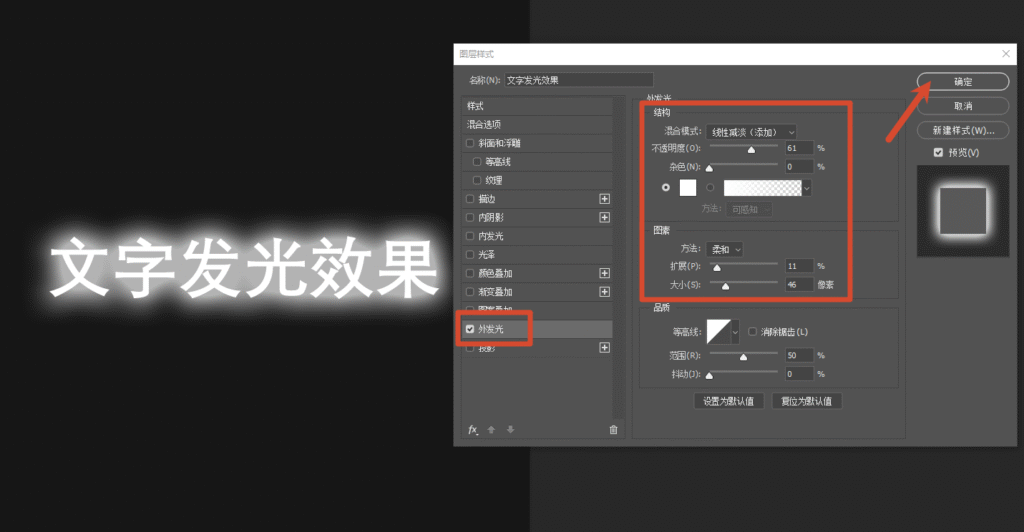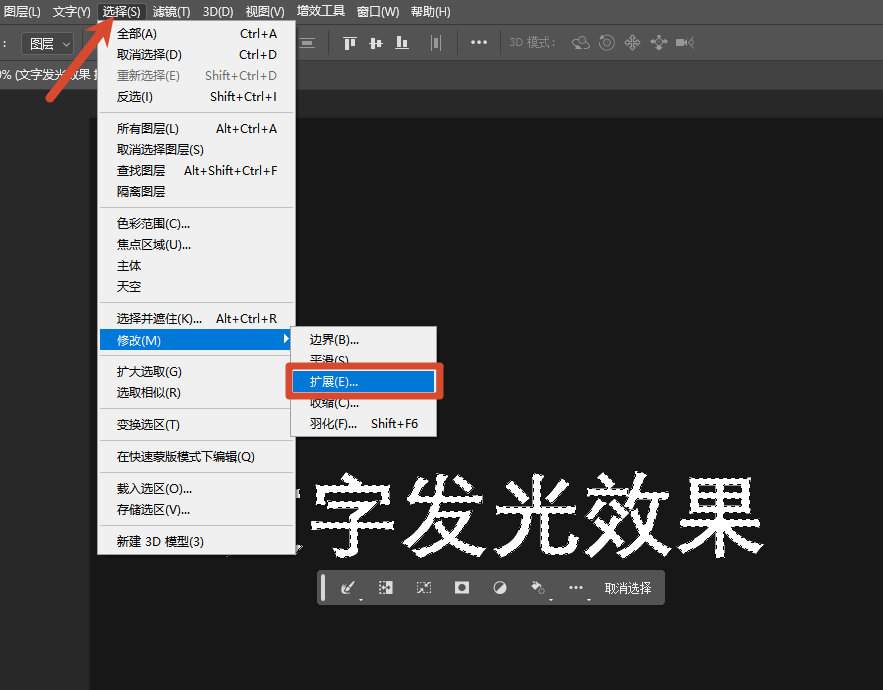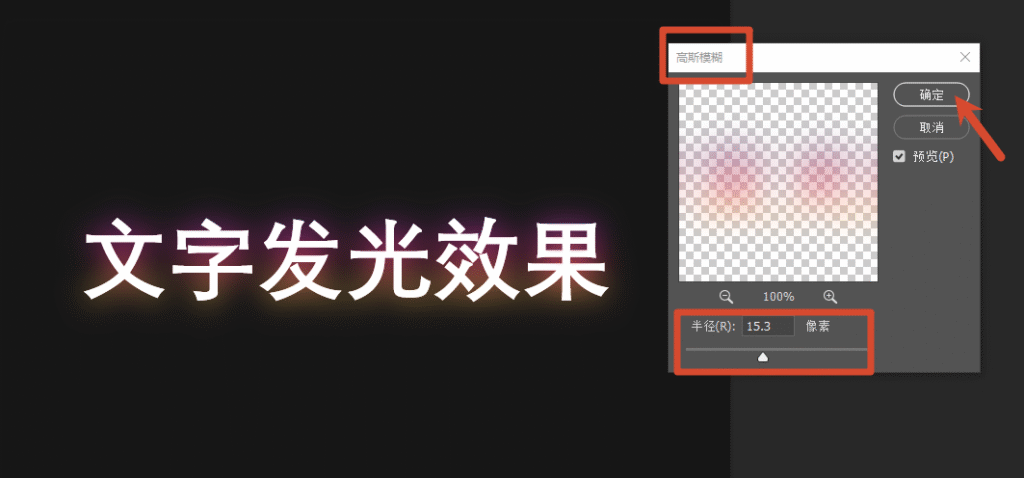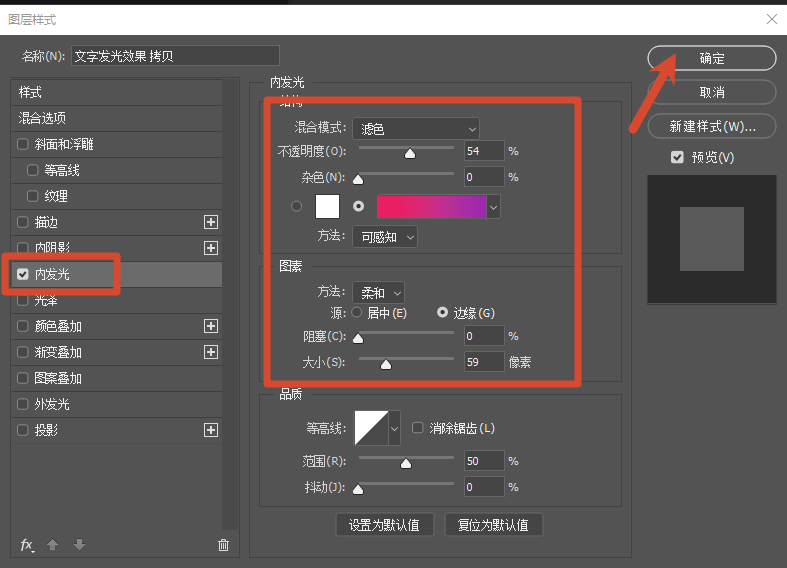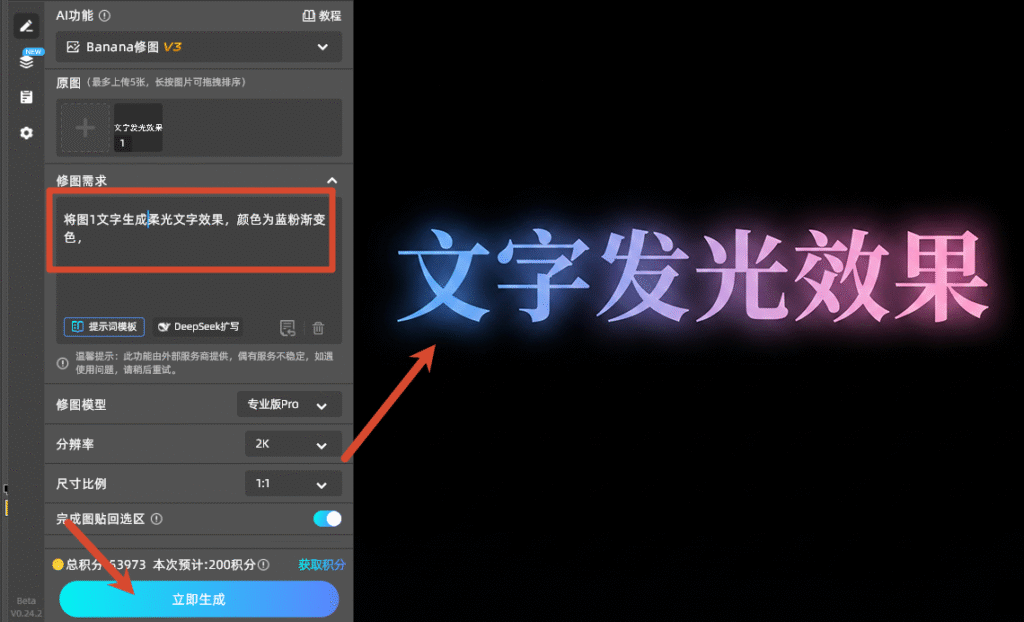
PS发光字体效果怎么做?3种方法从零教学
在海报设计、短视频封面、电商主图、赛博朋克风配图中,发光字体是提升画面氛围感、突出文字主体的常用特效。很多设计新手常常疑惑:ps发光字体效果怎么做?ps怎么做出自然不生硬的文字光晕?ps霓虹灯发光字体怎么制作?
本文结合专业设计实操经验,分享3种实用的PS发光字体制作方法,包含基础简易发光、高级霓虹发光、AI一键智能发光,适配PS2020-2026全版本,兼顾新手零基础操作和专业精细化调色,同时推荐高效便捷的StartAI插件,解决新手做光效卡顿、质感差、参数难调的痛点。
一、PS基础外发光制作:新手零基础简易发光字体
这是最简单、最通用的ps字体发光制作方法,依托PS自带图层样式,无需复杂操作,适合做简约柔光、日常海报发光文字,也是新手入门必学方法,适配绝大多数纯色背景、简约设计场景。
操作详细步骤:
新建画布输入文字:打开PS软件,快捷键Ctrl+N新建画布,建议深色背景(黑色、深灰色更凸显发光质感);点击左侧文字工具(T),输入需要制作特效的文字,调整字体、字号、字间距,优先选用粗体无衬线字体,发光层次感更强。
打开图层样式面板:鼠标双击右侧文字图层空白区域,弹出图层样式设置窗口,勾选左侧菜单栏中的外发光选项,这是制作基础发光的核心功能。
调整发光核心参数:混合模式推荐选择【线性减淡(添加)】,发光质感通透不发灰;不透明度控制在40%-75%,避免光线过曝;扩展数值5-15像素,模糊光晕边缘;大小根据文字尺寸调整,小字10-25像素、大字30-60像素。
调整图层模式参数
保存导出成品:参数调试完成后点击确定,简单的柔光发光字体就制作完成,快捷键Ctrl+Shift+S保存图片,支持PNG透明背景格式。
新手避坑技巧:很多人做的发光字体生硬廉价,核心原因是不透明度过高、发光颜色饱和度超标,日常设计建议选用低饱和柔光色。
二、进阶高级教程:PS霓虹灯发光字体效果
想要制作赛博朋克、夜店风、电竞风炫酷霓虹灯发光字体,单纯依靠外发光无法实现通透双层光感,需要结合选区修改、高斯模糊、图层混合模式制作,适合海报、Banner、短视频封面等高颜值设计场景。
操作详细步骤:
预处理文字图层:输入文字并排版完成,右键文字图层选择【栅格化文字】,将文字转为像素图层;按住Ctrl键点击图层缩略图,载入选区。
扩展制作光晕底衬:顶部菜单栏选择【选择-修改-扩展】,扩展量设置8-12像素,新建空白图层放置在文字下方,填充霓虹主色调。
选择-修改-扩展
模糊优化光效质感:选中光晕图层,点击【滤镜-模糊-高斯模糊】,模糊半径15-30像素,修改图层混合模式为【线性减淡】,强化发光通透感。
滤镜-模糊-高斯模糊
叠加细节光效:回到原文字图层,添加内发光图层样式,搭配深蓝色、玫红色等高饱和霓虹色,叠加渐变效果,打造双层光影层次感。
图层样式—内发光
痛点总结:进阶方法参数繁琐,需要反复调试模糊数值、混合模式,新手容易出现光效杂乱、色彩断层、画面模糊的问题,耗时久且对审美参数把控要求高。
三、懒人高效方法:StartAI插件一键制作高级发光字体
对于设计新手、兼职设计师、批量做图人群,手动调整图层样式、滤镜参数门槛高、效率低。这里推荐一款适配PS全版本的智能插件——StartAI插件,无需手动调试参数,一键生成柔光、霓虹、赛博、火焰等多种发光字体效果,完美解决ps发光字体怎么做才高级、自然、快速的难题。
1、StartAI内置Banana修图制作发光文字操作方法
打开Banana修图功能入口:安装完成StartAI插件并重启PS,完成文字输入与基础排版,无需做任何图层样式改动;在PS右侧StartAI插件面板中,找到Banana修图功能模块。
Banana修图
选中文字图层并进入特效模式:鼠标点击选中需要制作光效的文字图层,在Banana修图面板中,上传文字图层,填写修图需求:“将图1文字生成柔光文字效果,颜色为蓝粉渐变色”。
Banana修图效果图
一键生成:点击立即生成,无需手动调节参数,等待几秒即可完成文字发光效果制作,最后导出保存图片。
四、PS发光字体通用优化小技巧
1. 背景搭配:深色背景最适配发光字体,黑色、藏青色、深灰色能最大化凸显光影质感,浅色背景建议降低发光不透明度;
2. 字体选择:发光特效优先使用粗黑体、艺术粗体,纤细字体发光后容易模糊变形;
3. 色彩搭配:遵循同色系、低饱和原则,避免多种高饱和亮色混搭,防止画面杂乱刺眼;
4. 后期微调:制作完成后,可添加轻微曲线调色,提高画面对比度,让文字主体和光晕层次更分明。
五、总结
关于ps发光字体效果怎么做,本文整理了基础、进阶、AI智能三种制作方式:基础图层样式适合新手简单练手,进阶滤镜法适合专业炫酷特效制作,而StartAI插件凭借零门槛、高效率、高质感的优势,成为普通用户、自媒体人、兼职设计师的最优选择。